Tipografi menjadi bukan sekedar teks tetapi juga memilih gaya font yang merepresentasikan karakter brand. Pemilihan font dan kombinasi fontnya juga harus harmonis dan menciptakan kesan mudah dibaca. Kombinasi font sans serif dan serif paling sering ditemui dalam desain logo karena harmonis dan menciptakan keseimbangan visual.
Meski ada banyak variasi jenis font yang bisa digunakan, font dengan gaya huruf yang sederhana sering dipilih. Desain logo akan lebih sering menggunakan font sederhana agar mudah dibaca. Kombinasi dua font dengan gaya huruf sederhana tetapi masih memiliki gaya yang kontras akan efektif.
MENGAPA KOMBINASI FONT SANS SERIF DAN SERIF POPULER?
Font sans serif memiliki gaya huruf sederhana dan bersih, sehingga mudah dibaca dan fleksibel. Dalam logo kombinasi font sans serif tersebut harmonis dengan font serif yang memiliki ujung serif dengan gaya huruf sederhana. Ada beberapa alasan mengapa kombinasi font ini populer dalam desain logo, seperti:
Menciptakan Keseimbangan Visual
Kombinasi font akan memiliki dua gaya huruf sederhana dan bisa menciptakan keseimbangan visual. Font serif yang memiliki gaya huruf yang tradisional, formal dan elegan. Sementara sans serif memiliki tampilan huruf yang modern, bersih dan minimalis. Saat dikombinasikan kedua font yang sederhana tersebut akan menciptakan kseimbangan visual yang klasik dan modern.
Kontras yang Jelas
Kedua font memiliki gaya huruf sederhana tetapi bentuk yang berbeda sehingga menciptakan kontras. Kombinasi kedua font ini dalam desain logo akan menciptakan hirarki visual dan meningkatkan daya tarik visualnya. Kontras terlihat dari bentuk serif yang memiliki detail di ujung huruf, sementara sans serif memiliki huruf sederhana. Kombinasi font tersebut akan membuat logo lebih mudah dibaca dan lebih menarik.
Meningkatkan Hirarki Informasi
Biasanya desain logo selain memiliki teks nama brand juga memiliki tagline, tahun berdiri dan sub judul. Teks-teks ini harus memiliki gaya huruf berbeda untuk membedakan tingkat kepentingan informasi. Kombinasi font yang sederhana tersebut akan mudah dibaca sehingga membedakan teks nama brand dan tagline.
Fleksibel untuk Berbagai Gaya Brand
Kombinasi font sans serif dan serif dalam desain memiliki dua gaya huruf sederhana. Kombinasi font yang sederhana ini sering digunakan dalam logo karena mampu menciptakan desain logo yang fleksibel. Gaya huruf yang sederhana ini dapat digunakan untuk berbagai brand seperti logo perusahaan, logo start up dan fashion.
CONTOH LOGO KOMBINASI FONT SANS SERIF DAN SERIF
Teks dalam desain logo harus mudah dibaca, untuk itu perlu menggunakan kombinasi font yang sederhana. Kombinasi font serif dan sans serif dalam logo tersebut memiliki kombinasi font yang dengan huruf yang sederhana. Kombinasi font sans serif dan serif dalam berbagai brand berikut mudah dibaca dan menciptakan desain yang sederhana.
Logo Kiddy Grow
Desain logo tersebut memiliki jenis logo inisial sehingga memiliki style desain yang sederhana, termasuk penggunaan fontnya. Kombinasi font dalam logo inisial tersebut memiliki font sans serif dan serif. Kombinasi font dalam logo tersebut memiliki kontras yang baik dan mudah untuk dibaca.
Style font serif dalam desain logo memiliki gaya huruf yang agak tebal dan serif yang lancip. Gaya font serif yang bergaya modern dan memiliki gaya huruf yang kontras dengan font sans serif sederhana. Kombinasi font tampil kontras karena memiliki ukuran teks yang berbeda dan gaya font yang berbeda.
Logo War – We Are Collective
Desain logo yang hanya menggunakan tipografi tersebut juga menggunakan kombinasi font yang sederhana. Kombinasi font tersebut tampil kontras karena memiliki gaya huruf yang berbeda, termasuk memiliki ukuran yang berbeda.
Gaya font serif dalam desain logo tersebut memiliki bentuk yang unik, garis hurufnya melengkung dan memiliki huruf tebal. Font serif tersebut kontras ketika dipasangkan dengan font sans serif yang sederhana sebagai font taglinenya. Kontras ukuran juga menciptakan hirari visual yang jelas.
Logo Naomi Pilates Studio
Desain logo untuk pilates studio tersebut memiliki desain sederhana dan bergaya minimalis. Logo tersebut juga memiliki tipografi sebagai ikon logo utama agar nama brand mudah diingat. Kombinasi font serif dan sans serif menciptakan desain yang kontras dan bergaya elegan.
Font serif dalam logo tersebut memiliki font serif sederhana dan gaya huruf bersih sehingga mudah dibaca. Desain logo memiliki kombinasi font sans serif dan serif yang kontras dengan font yang sederhana. Nama brand mudah dibaca dan memiliki kombinasi siluet orang sedang pilates sehingga tampil elegan dan relevan.
Logo Bun.Azz
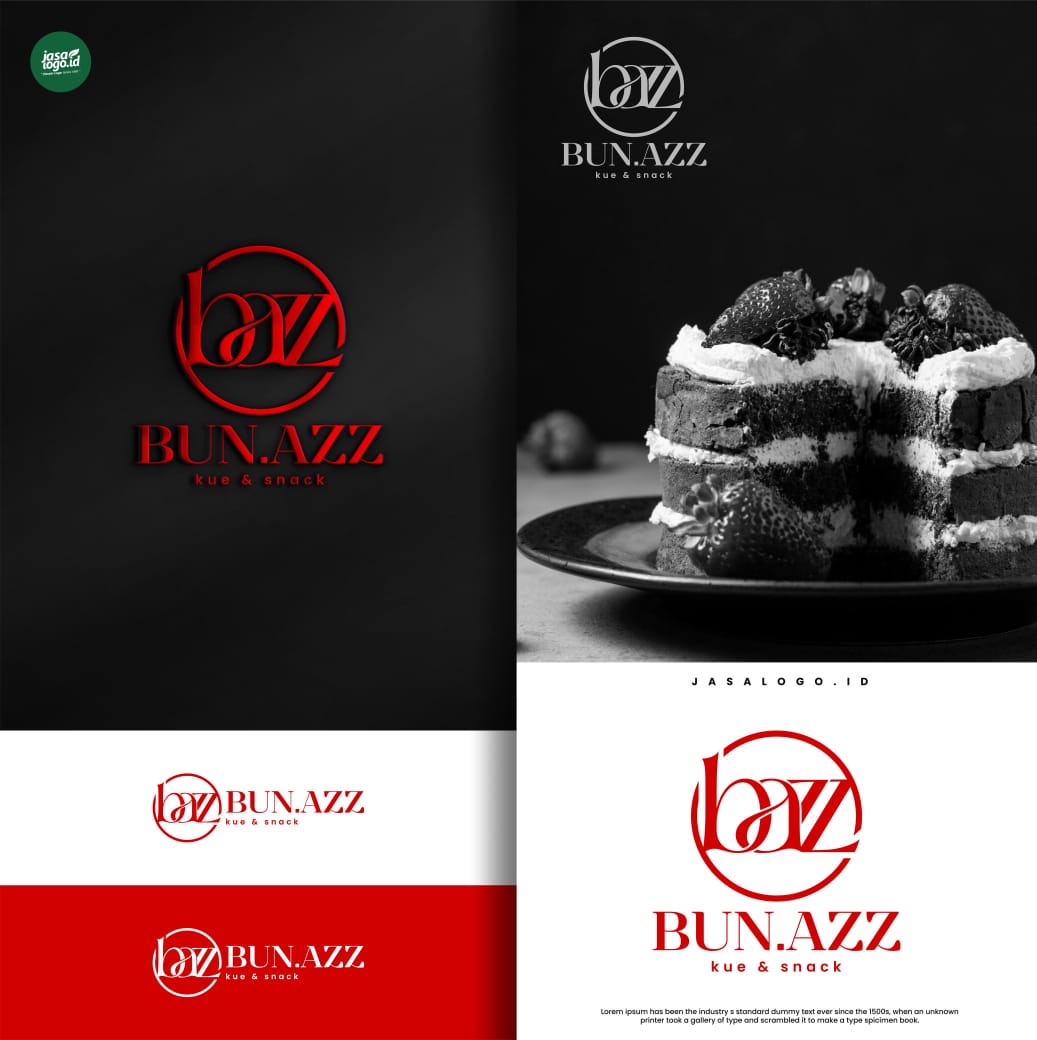
Desain logo untuk bisnis bakery tersebut memiliki kombinasi font sederhana yaitu serif dan sans serif. Tipografi serif dalam logo tersebut memiliki jenis font serif modern yang elegan dan mudah dibaca. Font serif dipasangkan dengan font sans serif yang sederhana sehingga harmonis.
Memperkuat Pesan Brand
Kombinasi font serif dan sans serif dapat menciptakan dua kesan berbeda yaitu modern dan klasik. Font akan membuat logo tampil sederhana dan memiliki nuansa yang klasik dan modern.
Desain logo paling sering memiliki kombinasi font serif dan sans serif karena akan menciptakan tipografi yang sederhana. Kombinasi dua font yang sederhana tersebut menciptakan kontras yang jelas dan hirarki visual. Perbedaan jenis font berguna membedakan teks nama brand dan tagline sehingga mudah dikenali oleh audiens.